30款细而优雅的连笔英文字体
Wertign
一款细而优雅的书法英文字体,很适合用在华丽的婚礼请柬或名片上。
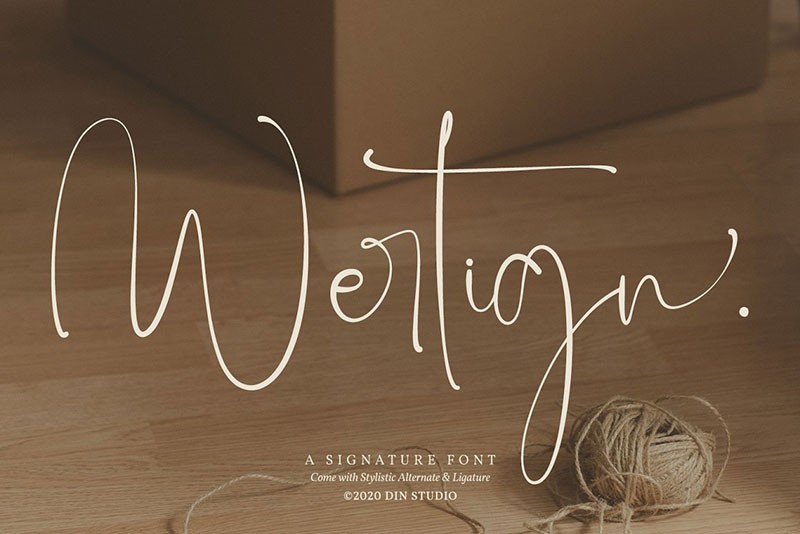
Romellast
TheMonse(可商用)
一种手工书法字体。它的特点是具有自然的手写外观和跳动的基线。非常适用于贺卡、签名风格的标志、奢侈品营销、引言、海报等。
Malvyew
一款休闲别致的字体,具有手工书法风格,装饰性的字符和舞动的基线! 在贺卡、品牌材料、名片、引言、海报等邀请函上非常漂亮!!
brillyo
一种优雅而自然现代字体,具有手工书法风格。
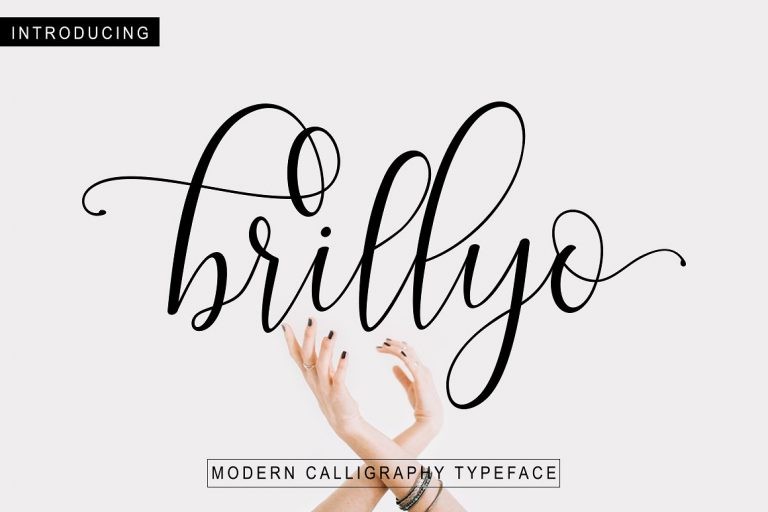
Cataline Script
一款时尚的书法字体,带有爱的气息。这种字体的特点是变化的基线、流畅的线条、现代和有深度的爱。
Rosanthie
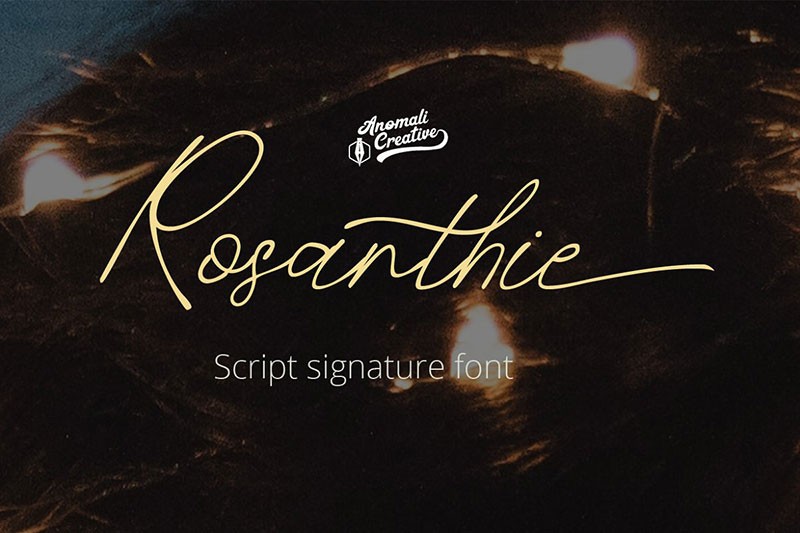
Meghatone Signature
一个轻盈而有趣的字体,具有很酷的转折。它将是为任何设计添加自然手写触摸的理想字体。
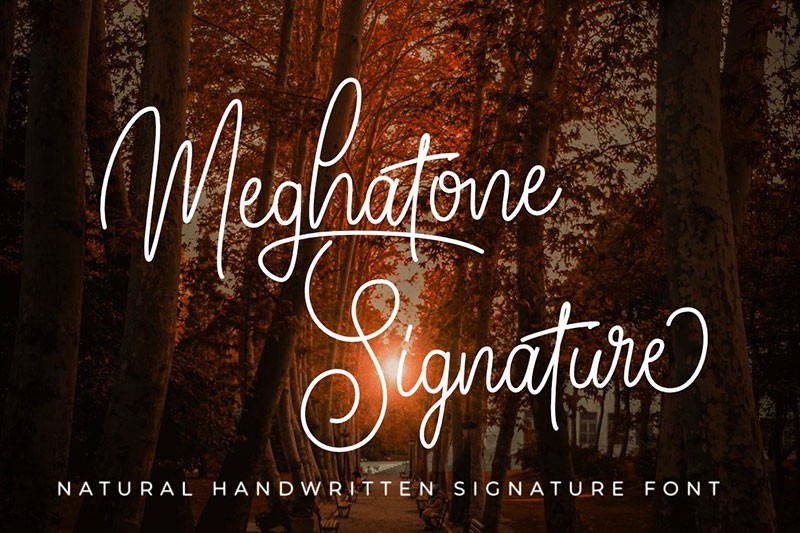
Sutton Brent
时尚的签名手写字体体。具有自然和时尚的笔画。
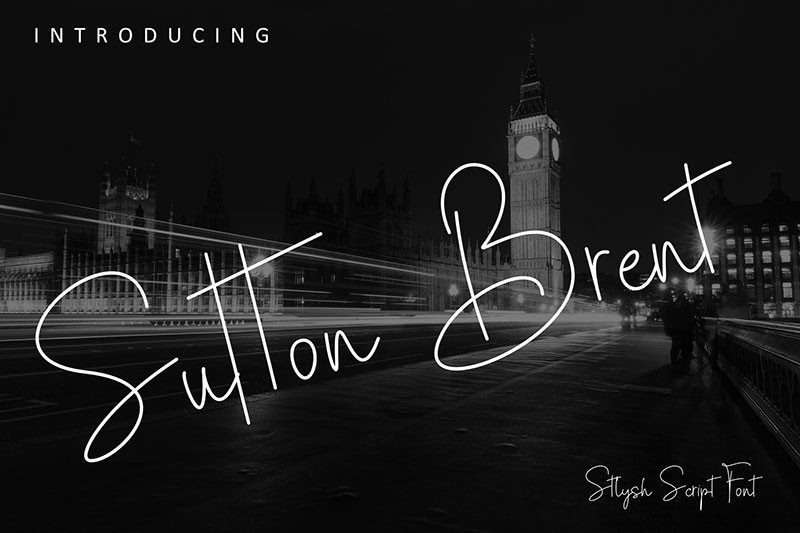
Kimberley Waterfall
干净简洁的手写签名字体,你会爱上它令人难以置信的多变风格。
Indesign Signature
一个优雅的现代手写字体。
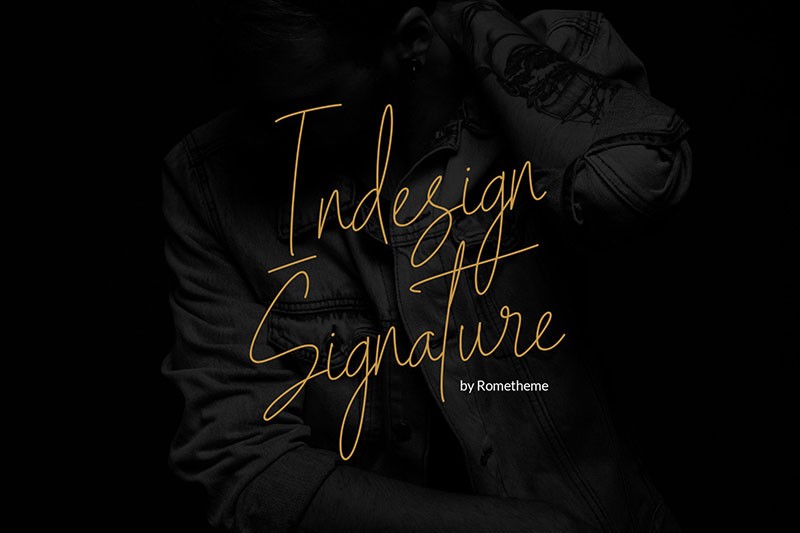
Wishloved
一种休闲时尚的手写字体,自然的线条运动使它漂亮而优雅。这种签名字体非常适合用于封面、水印、品牌、名称、名片、产品、标志等。
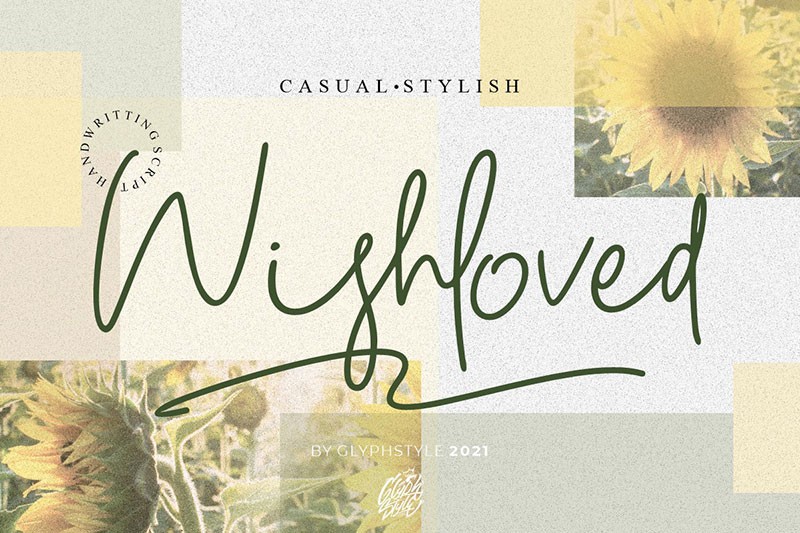
Beatrix Signature
一种优雅和时尚的手写英文字体。
Holdsmith
一种极简主义的现代优雅字体。非常通用的字体,在大尺寸和小尺寸中都有很好的效果。
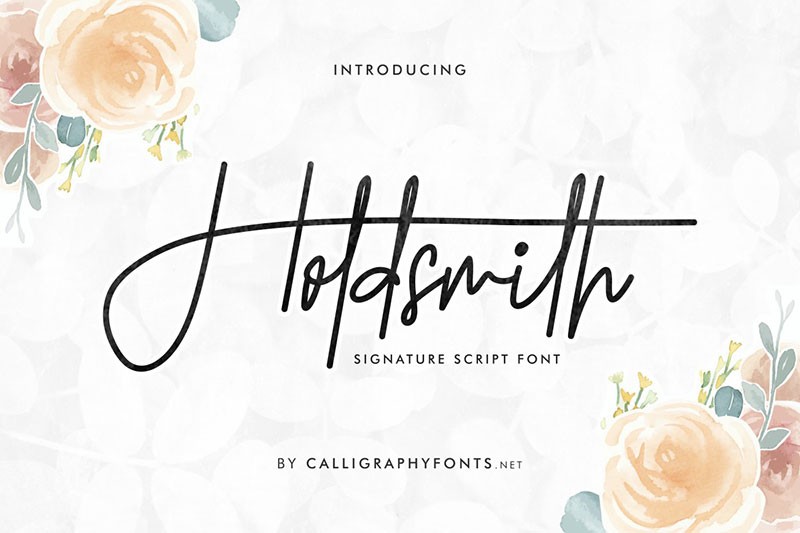
Las Antonio
一种现代和流畅的休闲签名时尚手写字体。
Flow Perfect
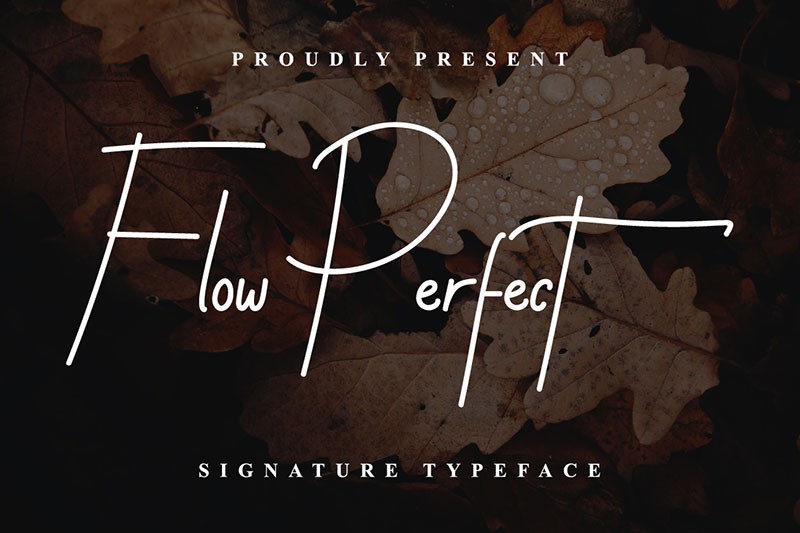
Jean Jingga
Boheme Floral
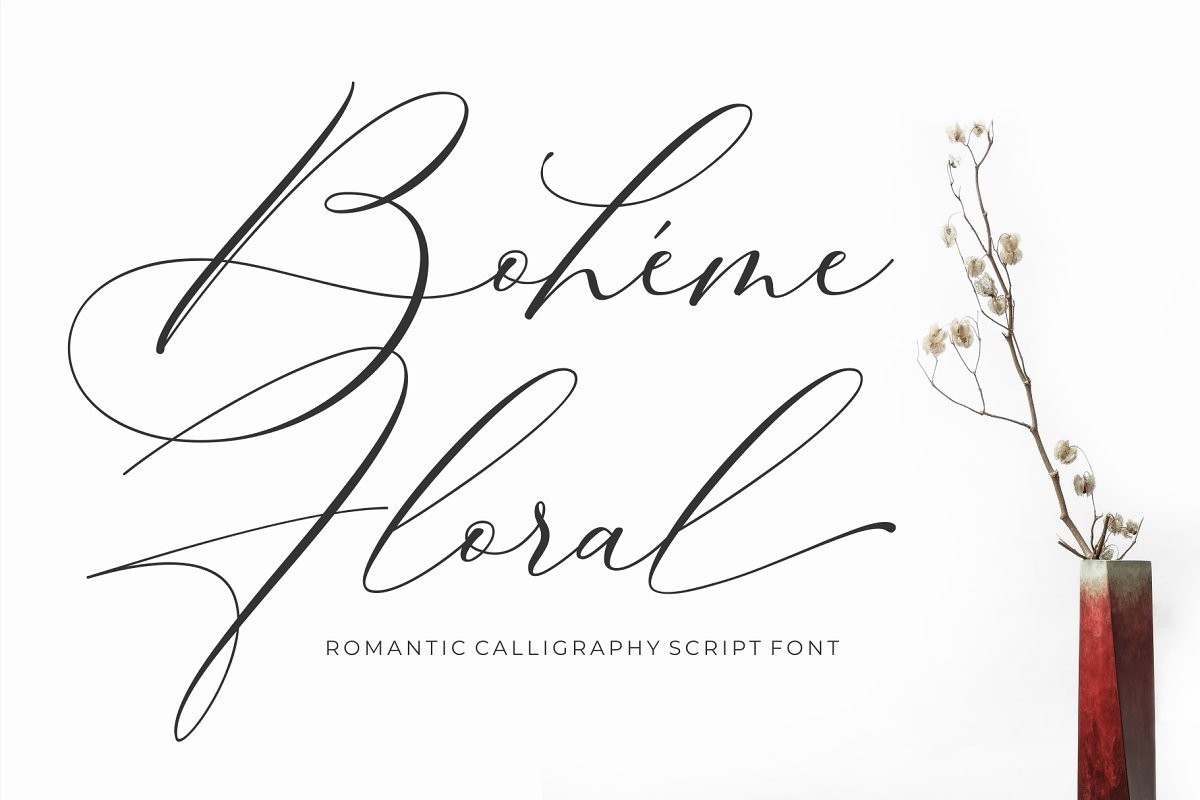
Keylista Robin
一种浪漫的手写字体,适用于任何项目,如:商标、品牌设计、家居设计、产品包装等。
Autopilot
一个优雅和流畅手写签名字体。
Badriyah
一款简单、优雅、有品位的连笔英文字体。
Hayley Signature
Routhem
Gilliany
现代风格签名英文字体,具有整洁的笔迹风格,每个字母和连接词的形状都有自己的特点,适合各种需求。
kristallian
文字看起来很美,每一个字母都经过精心设计。
Matthew
一款优美的现代连笔英文字体,结合了经典和现代的书法风格。
Signatures
一款模拟真实签名英文字体,该字体适用于任何设计,如品牌,时尚,婚礼等。
Quake Love
这款字体非常适合用于婚礼明信片。
Sentilum
一种轻松和可爱的手写字体。
Red Chute
这个字体是用毛笔制作的,可以实现完美的手写。这个字体有一个独特的特点,字母之间不太紧密。 使字体看起来更漂亮。